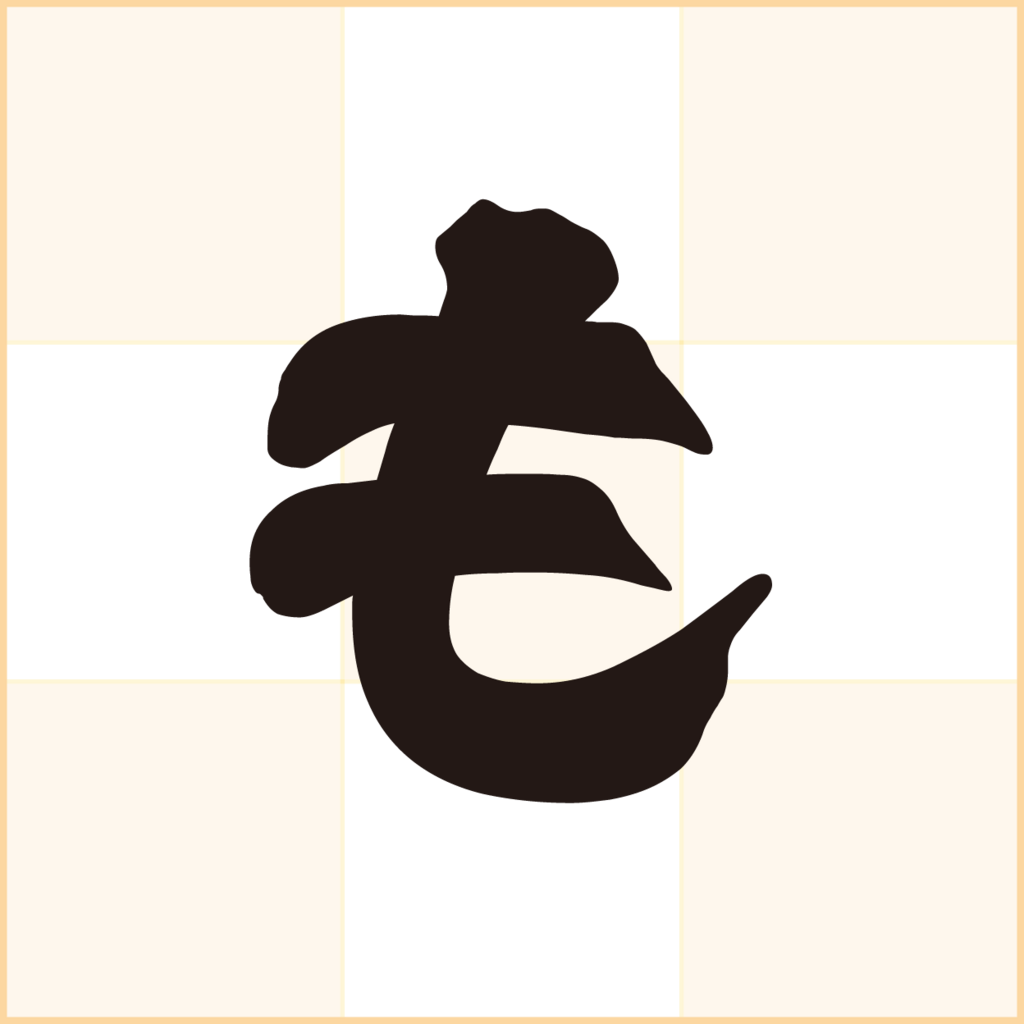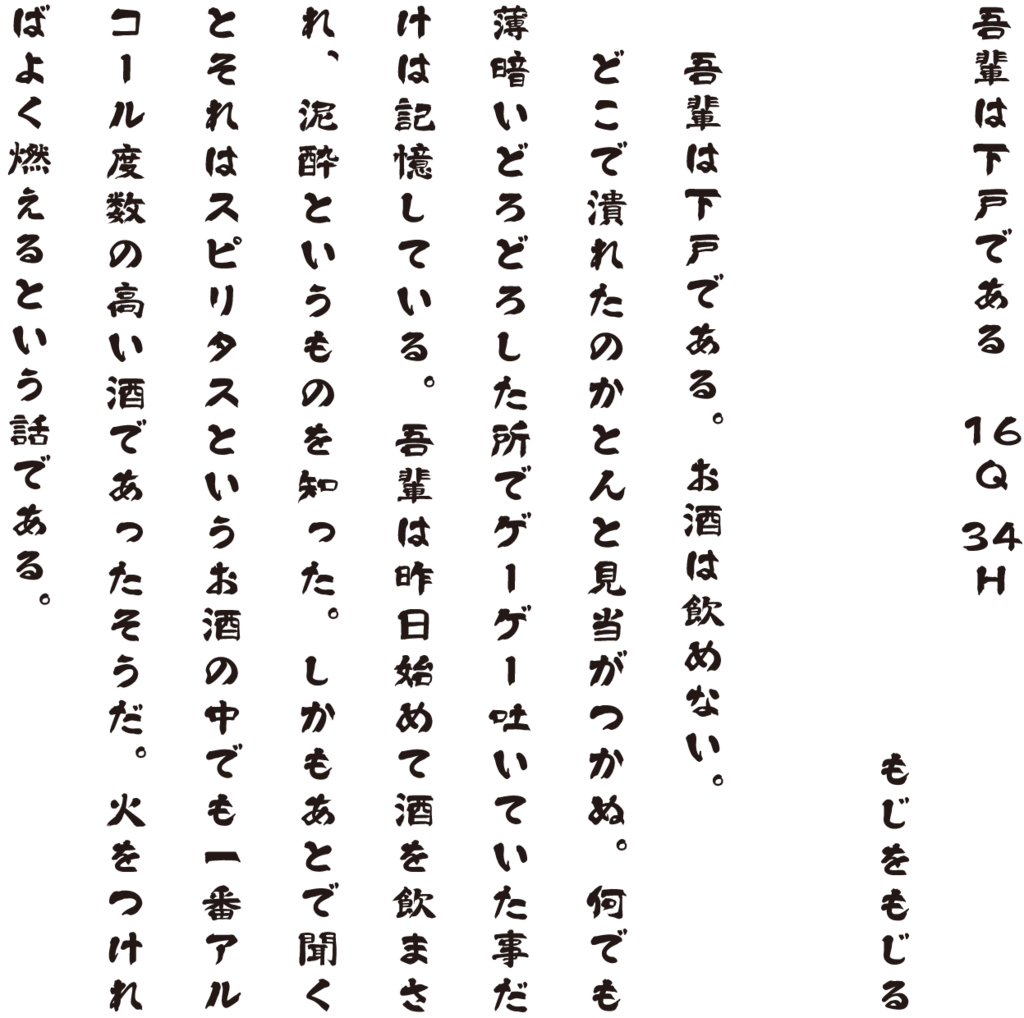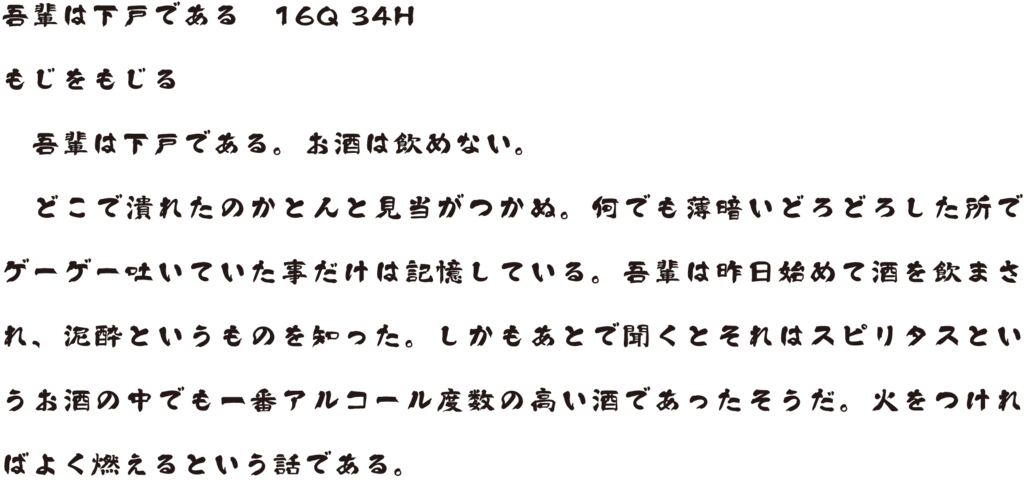
毛筆フォント・大河体
筆文字ならではの勢いや力強さを表現した女性書道家による筆系の書体。筆は鼬の毛の筆を使用。その特徴である優れた弾力性が、起筆や払いの勢いに見事に反映されると共に、流れるような筆運びにも色濃くあふれている。豪快かつ極太な筆画の中に、どことなく女性書道家らしい繊細さや柔らかさも感じられる。
毛筆フォント・大河体の組見本
ホラーに合うフォント「大河体」
大河体は割とおどろおどろしいのでホラー系のフォントとしても使えそうだ。